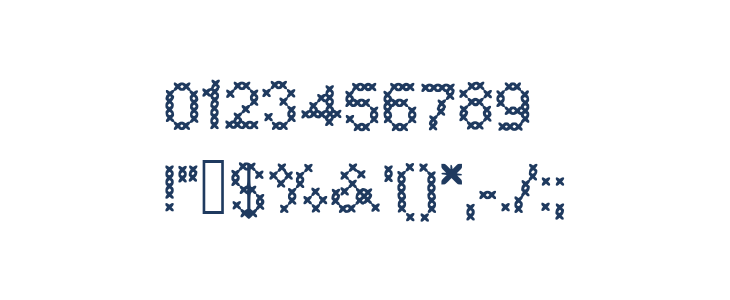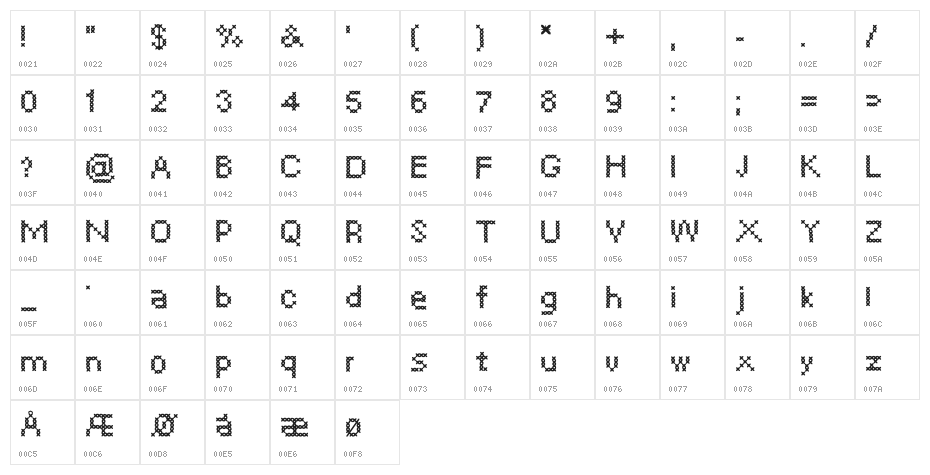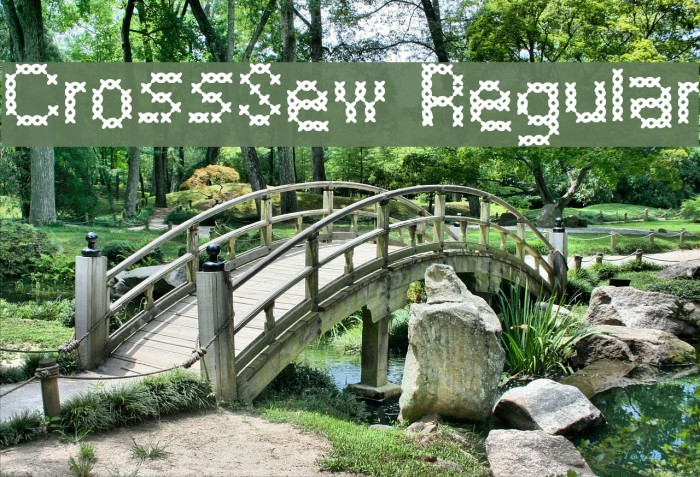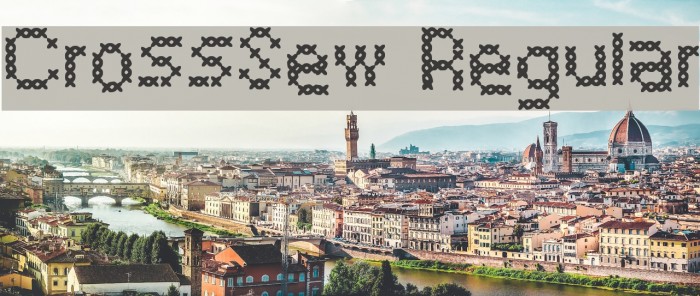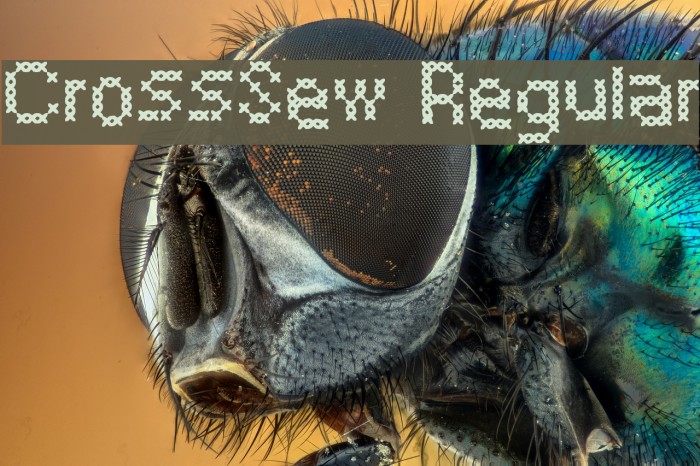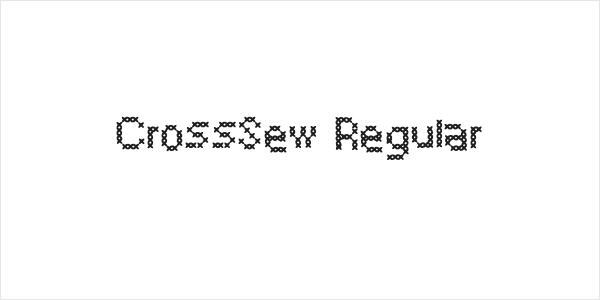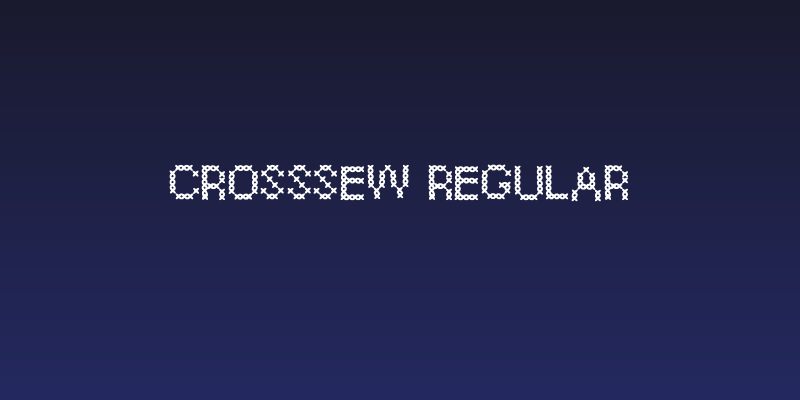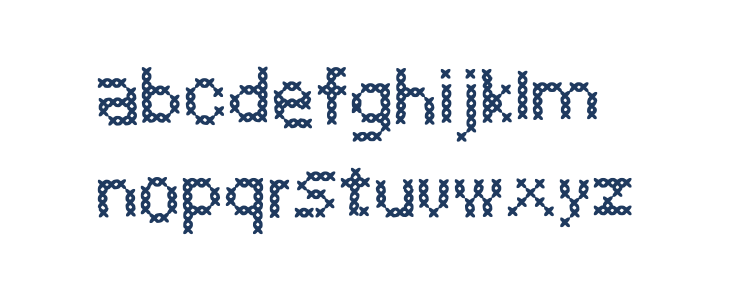
CrossSew Regular Font
Fonts by Bård Oskar Angelskår
| الفئات | Decorative |
| النمط العام | Vintage |
| حالة الاستخدام | Logos, Headlines, Decorative text |
| مشاريع مقترحة | Ideal for craft projects, DIY invitations, textile designs, and any creative work that requires a handmade or vintage touch. |